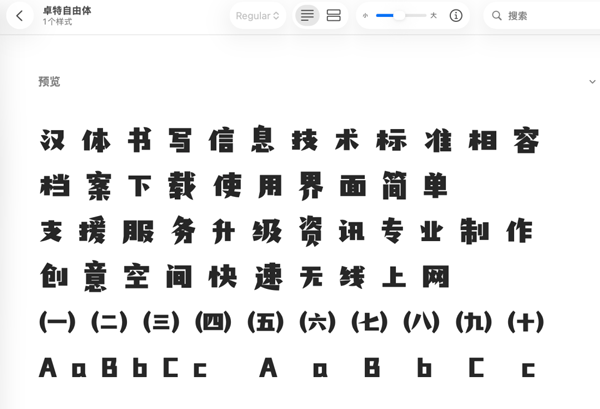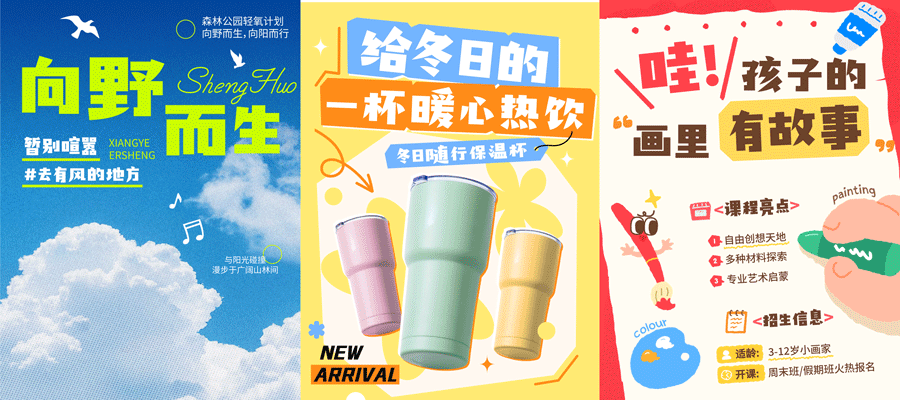
卓特自由体是卓特视觉携手国内知名字体设计师刘兵克专为创意人群打造的一款风格迥异的免费可商用开源字体。
卓特视觉是 Adobe Stock 中国区官方合作伙伴,为用户提供图片、插画、矢量等高清版权素材;刘兵克则是国内著名字体设计团队“字体帮”的创始人,有 10 多年字体设计经验。两者强强联合共同打造了三款卓特视觉开源字体,完全免费供大众使用。
| 字体名称 | 笔画与结构特征 | 推荐应用场景 |
|---|
| 卓特自由体 | 字形结构宽阔,大小不一,笔画粗实有力,几何感强 | 娱乐视觉、综艺字幕、短视频封面、创意 Banner |